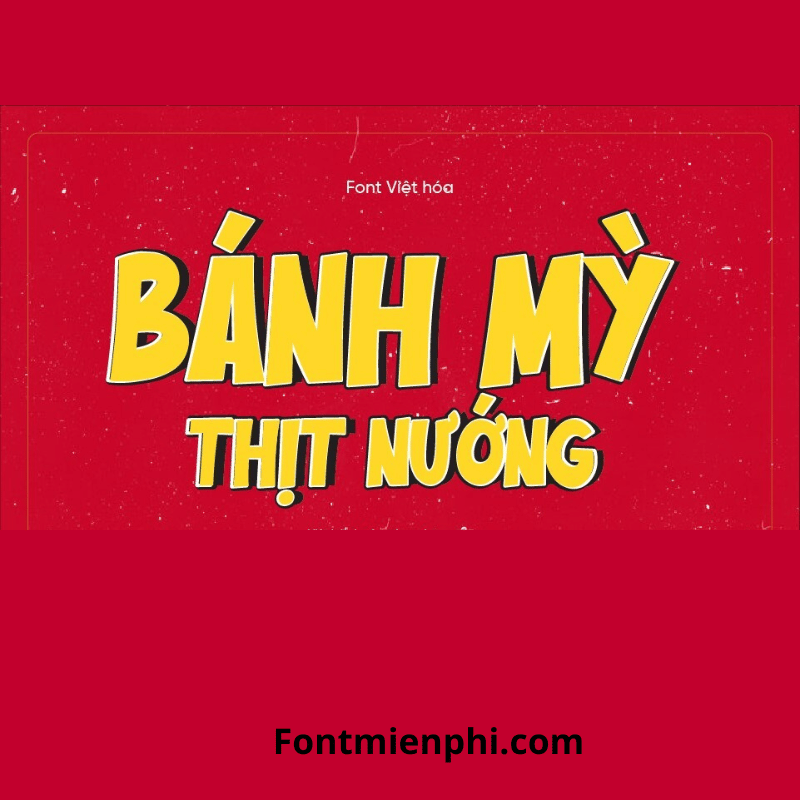
Font Việt hóa 1FTV VIP Bazinga!
Font Việt Hóa 1FTV VIP Bazinga! – Phong Cách Độc Đáo Cho Thiết Kế
Font Việt hóa 1FTV VIP Bazinga! là bộ font chữ độc quyền, được thiết kế dành riêng cho cộng đồng sáng tạo Việt Nam. Với phong cách cá tính, nét chữ mạnh mẽ và khả năng tương thích tiếng Việt hoàn hảo, font chữ này trở thành lựa chọn hàng đầu cho dân thiết kế, game thủ và content creator.
• Thiết kế độc đáo: Nét chữ sắc sảo, phá cách, phù hợp với poster, logo, banner hoặc game.
• Hỗ trợ tiếng Việt: Bảng mã Unicode đầy đủ, đảm bảo hiển thị rõ ràng mọi dấu tiếng Việt.
• Đa dạng ứng dụng: Dùng cho Photoshop, Illustrator, game mod, video intro và nhiều dự án sáng tạo khác.
• Tăng tính thẩm mỹ cho sản phẩm thiết kế.
• Phù hợp với nhiều phong cách, từ cá tính đến hiện đại.